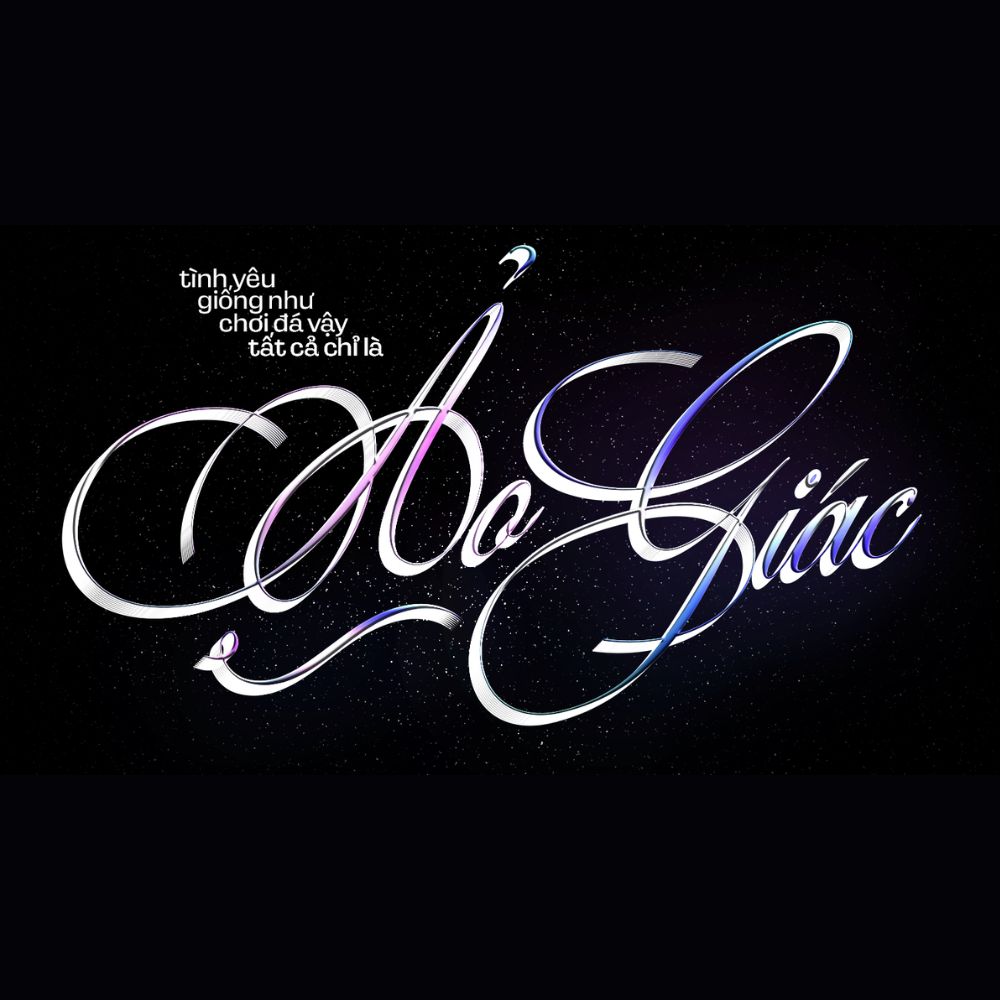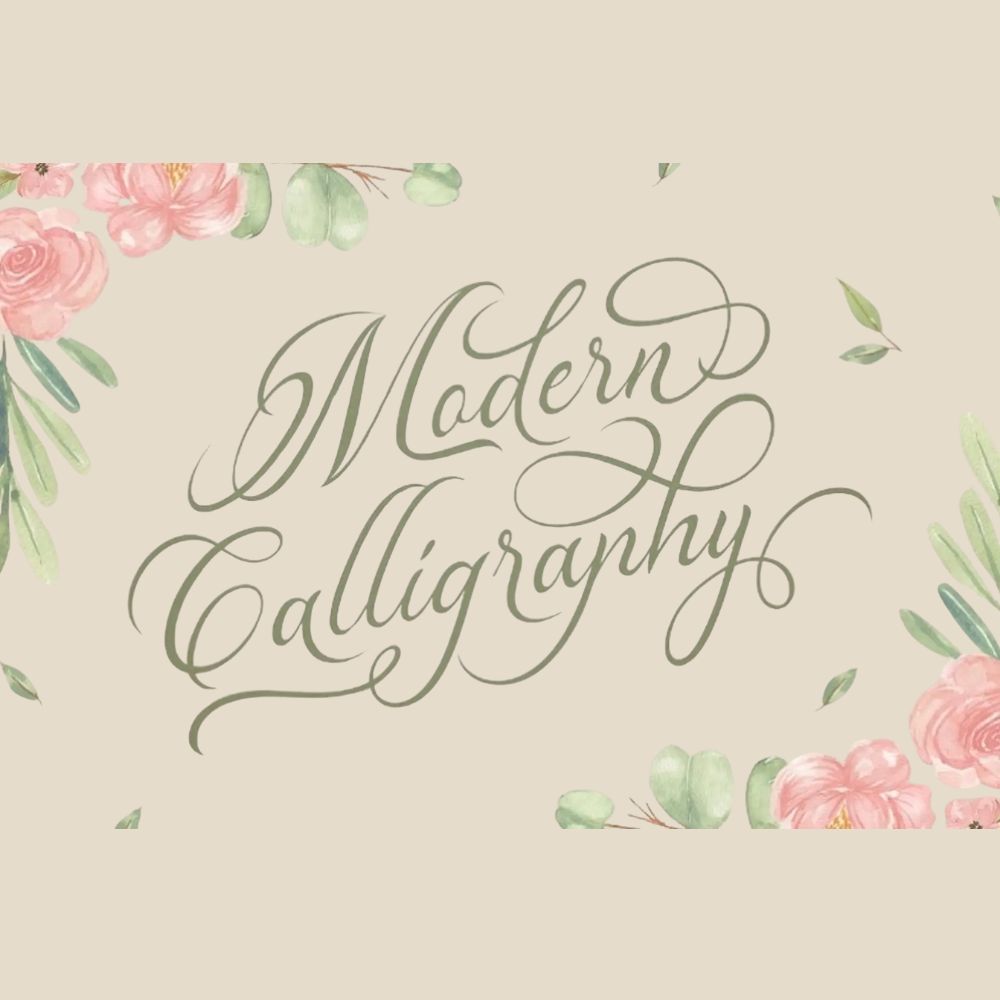
Bạn đang tìm kiếm font calligraphy Việt hóa đẹp để sử dụng trong thiết kế và in ấn? Đây là dòng font chữ nghệ thuật nổi bật với nét viết mềm mại, uyển chuyển như chữ viết tay, rất phù hợp cho các thiết kế mang tính thẩm mỹ cao. Trong bài viết này, In Viva sẽ cung cấp thông tin chi tiết, hướng dẫn tải và cách sử dụng font chữ calligraphy việt hóa hiệu quả.
Font Calligraphy mang đến vẻ đẹp uyển chuyển, tinh tế, giúp các thiết kế từ thiệp mời đến bao bì sản phẩm trở nên sang trọng và đầy tính nghệ thuật. Việc sử dụng phiên bản Việt hóa giúp bạn hoàn toàn yên tâm về khả năng hiển thị tiếng Việt mượt mà, không lỗi dấu, phù hợp cho mọi dự án đồ họa sáng tạo. Dưới đây là một số font Calligraphy Việt hóa đẹp phổ biến:
Tên font Đặc điểm
Ứng dụng
Bellissima Script Pro
Hơn 2000 ký tự mở rộng, phong cách hoàng gia, tinh tế Thiệp cưới, chứng chỉ, tiêu đề sang trọng
Desirable Calligraphy Chữ viết tay, mềm mại, sang trọng
Thiệp cưới, thiệp mời, thiết kế cao cấp
Pinyon Script
Nét thanh nét đậm rõ ràng, lãng mạn, cổ điển Thiệp cưới, poster cổ điển
SVN-Nautica Chữ viết tay mềm mại, uốn lượn
Thiệp cưới, tiêu đề, logo thương hiệu
Oleo Script Nét chữ độc đáo, hiện đại, thân thiện
Logo, menu, quote, poster
Bukhari Script Chữ đậm, khỏe khoắn nhưng mềm mại
Thiết kế logo, banner, social media
Madelyn
Phong cách tự nhiên, như nét bút lông Banner, tiêu đề sáng tạo, social media
Araulga Laudery Regular Nhiều ký tự thay thế uốn lượn, tươi mới
Logo, quote, menu, poster
Satisfy
Rõ ràng, dễ đọc nhưng vẫn quyến rũ Trích dẫn, tiêu đề phụ, social media
Nickainley Nét chữ đều, monogram kinh điển, dễ nhìn
Logo, tiêu đề phụ, trích dẫn
Đặc điểm nổi bật của font Calligraphy Việt hóa
Font Calligraphy là kiểu chữ mô phỏng nét bút viết tay nghệ thuật (thư pháp hiện đại), thường có các đường nét thanh – đậm rõ ràng, tạo cảm giác mềm mại và tinh tế.
Calligraphy font Việt hóa là phiên bản đã được tối ưu đầy đủ dấu tiếng Việt, giúp người dùng dễ dàng sử dụng trong thiết kế mà không gặp lỗi hiển thị. Đây là lựa chọn lý tưởng cho designer, marketer và doanh nghiệp cần tạo điểm nhấn cảm xúc trong ấn phẩm.
Font calligraphy được yêu thích nhờ giá trị thẩm mỹ cao và khả năng ứng dụng linh hoạt:
• Nét chữ mềm mại, uyển chuyển như viết tay
• Có sự kết hợp giữa nét thanh và nét đậm tạo chiều sâu
• Mang phong cách nghệ thuật, sang trọng và tinh tế
• Nhiều font có ligature (nét nối chữ) đẹp mắt
• Hỗ trợ tiếng Việt đầy đủ, dễ sử dụng
• Phù hợp cho thiết kế cần cảm xúc và điểm nhấn
Font chữ Calligraphy Việt hóa tinh tế sang trọng
Ứng dụng của font Calligraphy trong thiết kế
Font chữ calligraphy Việt hóa được sử dụng rộng rãi trong nhiều lĩnh vực:
• Thiết kế thiệp cưới, thiệp mời
• Trang trí bao lì xì, ấn phẩm Tết
• Thiết kế logo thương hiệu thời trang, mỹ phẩm
• Bao bì sản phẩm cao cấp
• Poster, banner nghệ thuật
• Social media: caption, quote, cover
• Trang trí scrapbook, album ảnh
Font đặc biệt phù hợp với các thiết kế cần sự mềm mại, cảm xúc và tính cá nhân hóa cao.
Font Việt hóa Calligraphy hỗ trợ thiết kế và in ấn chuyên nghiệp
6 lưu ý khi sử dụng font Calligraphy Việt hóa
Để khai thác tối đa hiệu quả thẩm mỹ và đảm bảo chất lượng khi thiết kế – in ấn, bạn nên lưu ý những điểm sau:
• Sử dụng font chủ yếu cho tiêu đề, điểm nhấn hoặc nội dung ngắn, tránh dùng cho đoạn văn dài vì sẽ khó đọc.
• Kết hợp với các font sans-serif đơn giản để cân bằng bố cục và tăng tính dễ đọc.
• Ưu tiên dùng kích thước lớn để làm nổi bật nét chữ mềm mại và chi tiết của font.
• Chuyển font sang outline trước khi in để tránh lỗi hiển thị trên các thiết bị khác.
• Kiểm tra hiển thị tiếng Việt trước khi xuất file, đảm bảo các dấu và ký tự đặc biệt hiển thị chính xác.
• Sử dụng file font chất lượng cao để đảm bảo độ sắc nét, đặc biệt khi in ấn hoặc phóng to.
Việc tuân thủ những lưu ý này sẽ giúp phông chữ Calligraphy Việt hóa phát huy tối đa giá trị thẩm mỹ và chuyên nghiệp trong mọi thiết kế.
Font chữ Calligraphy viết tay Việt hóa bay bổng tạo điểm nhấn cho tiêu đề
Font Calligraphy phù hợp thiết kế gì?
Phù hợp thiệp cưới, bao bì, poster, social media và các thiết kế nghệ thuật.
Có nên dùng font Calligraphy cho nội dung dài không?
Không nên, vì nét chữ phức tạp sẽ gây khó đọc.